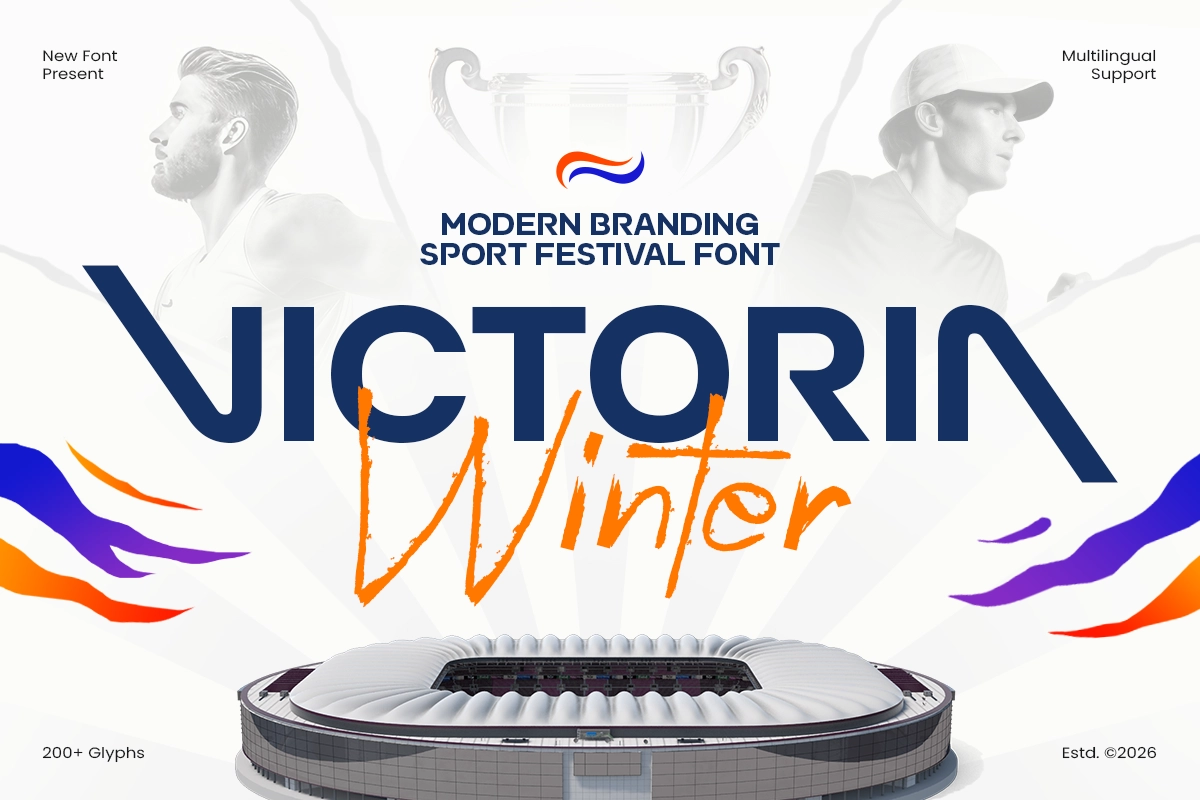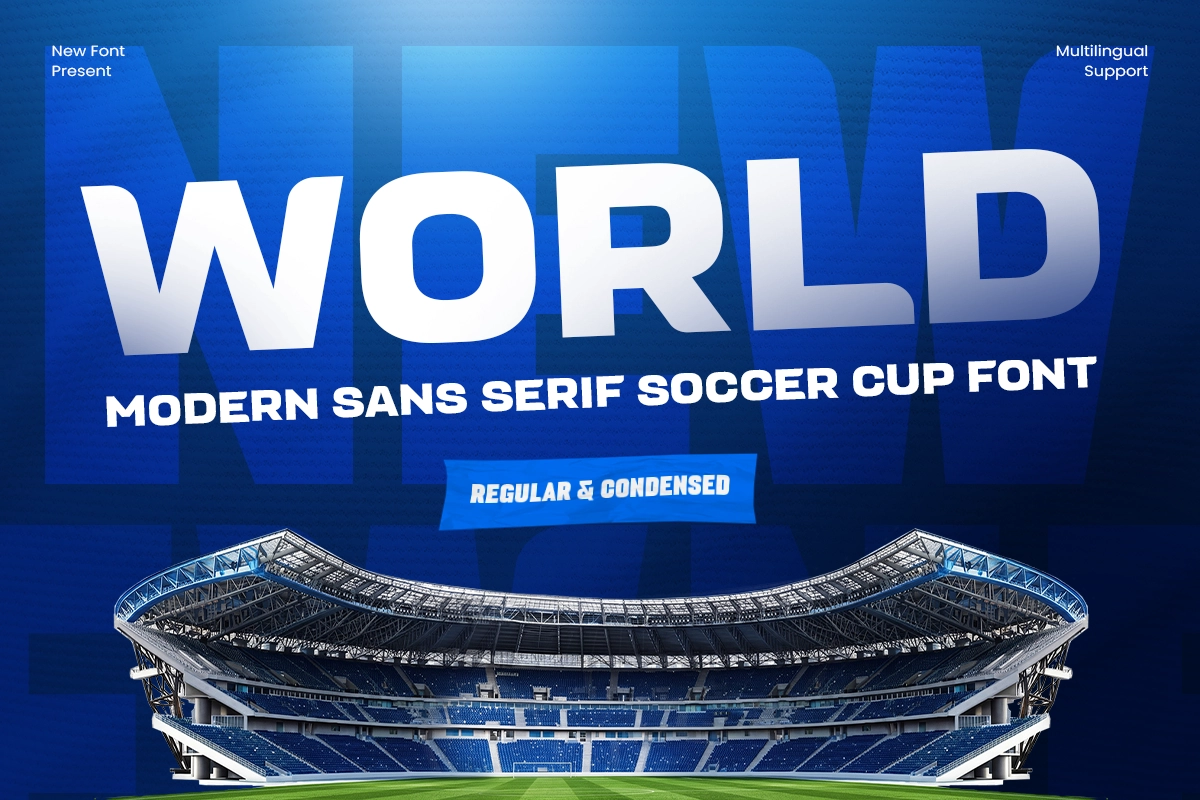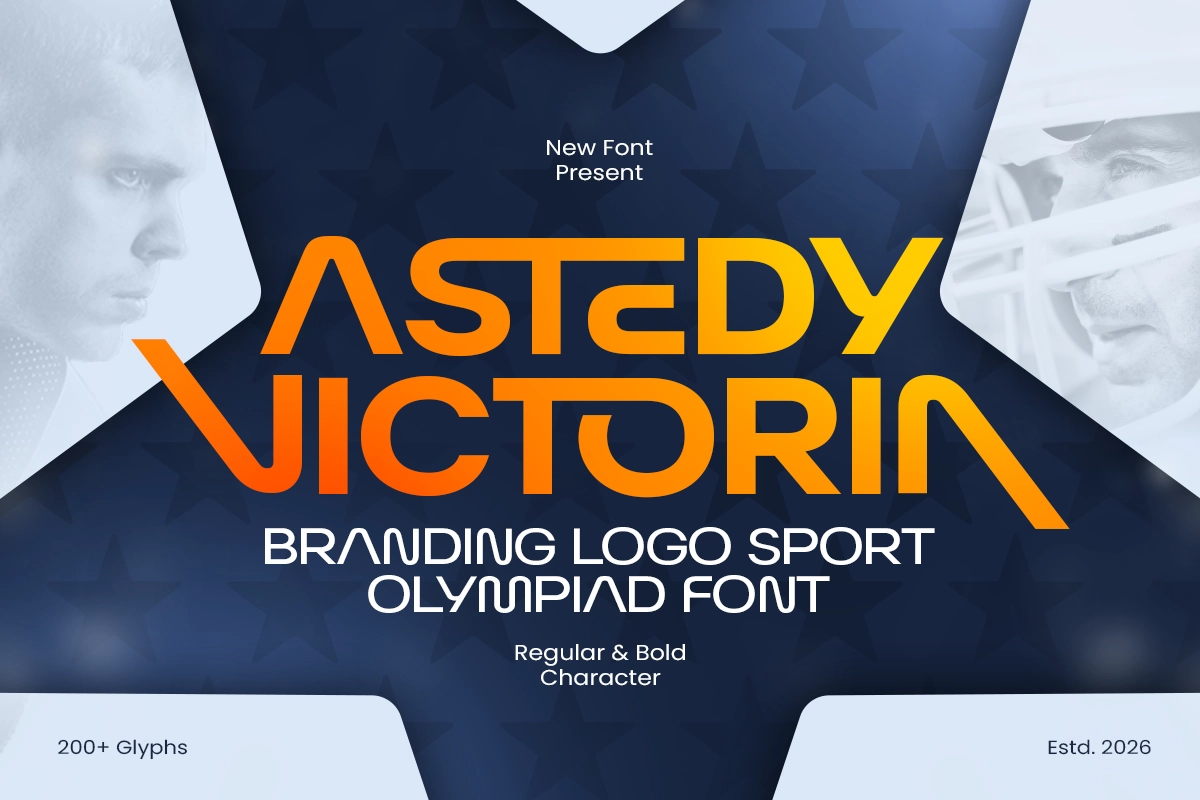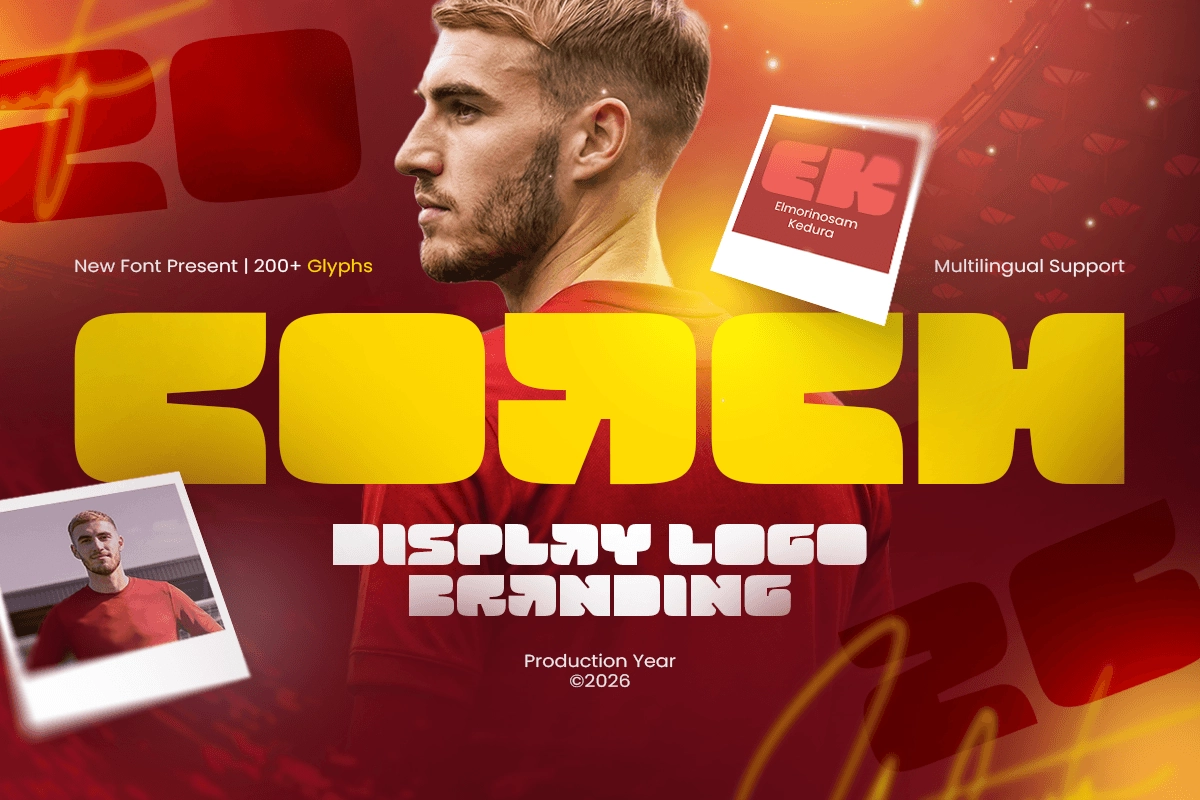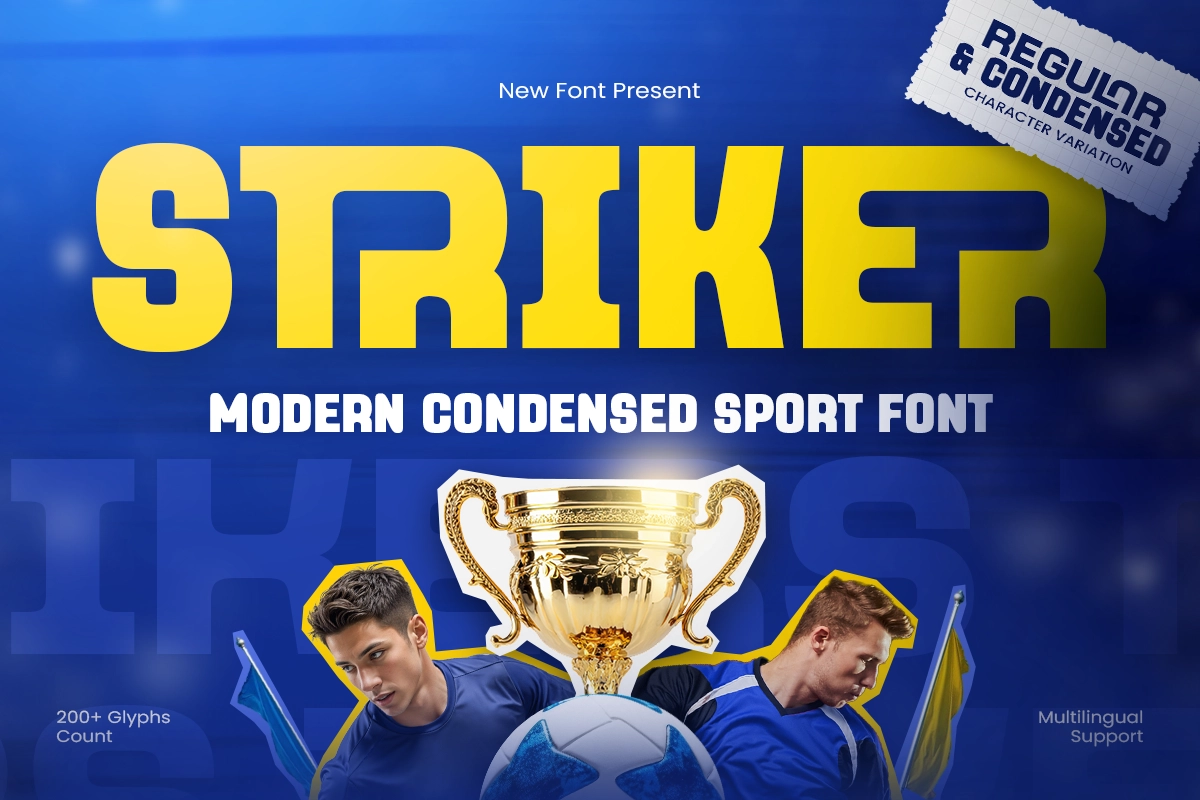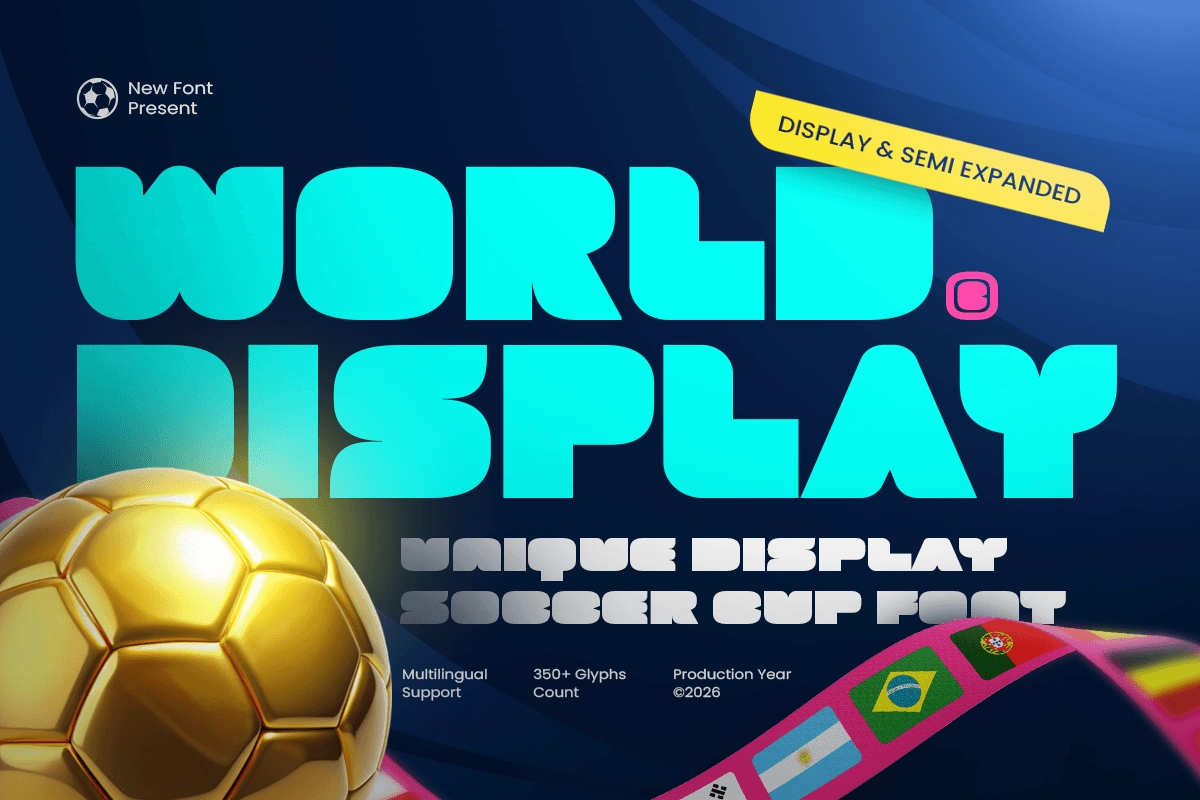
Font apa yang digunakan untuk Piala Dunia 2026?
Font Piala Dunia 2026 menggunakan typeface custom eksklusif milik FIFA yang dirancang khusus untuk identitas visual turnamen ini. Panduan ini menjelaskan mengapa desainer sebaiknya menghindari meniru font resmi tersebut, sekaligus merekomendasikan alternatif font olahraga berlisensi yang cocok untuk poster sepak bola, mockup jersey, grafis matchday, dan branding tim.
Font apa yang digunakan untuk Piala Dunia 2026?
FIFA World Cup bukan sekadar turnamen sepak bola. Setiap edisi menghadirkan sistem identitas visual yang lengkap. Mulai dari logo, warna, maskot, poster, jersey, hingga tipografi yang membentuk keseluruhan bahasa visual yang tampil di stadion, layar siaran, merchandise, dan kampanye digital.
FIFA World Cup 2026 menjadi salah satu edisi paling dinantikan karena diselenggarakan di tiga negara sekaligus: Amerika Serikat, Kanada, dan Meksiko. Dengan skala sebesar itu, identitas visual harus terasa kuat, modern, dan mudah dikenali dalam berbagai format. Tipografi menjadi elemen penting yang membawa identitas tersebut ke layar stadion, grafis siaran, merchandise, media sosial, dan materi kampanye resmi.
Bagi para desainer, font Piala Dunia 2026 menarik perhatian karena menghadirkan nuansa berani, sporty, dan berenergi tinggi yang khas dari ajang olahraga global. Namun, menggunakan typeface resmi tersebut, menjiplak bentuk hurufnya, atau meniru gayanya terlalu dekat dapat menimbulkan risiko hukum dan masalah branding. Pendekatan yang lebih aman adalah mempelajari arah visualnya, lalu memilih font olahraga berlisensi dengan energi serupa untuk poster sepak bola, mockup jersey, grafis matchday, branding tim, dan desain bertema turnamen.
Dengan turnamen yang digelar di tiga negara dengan budaya visual yang berbeda-beda, peluang kreatif terbuka sangat luas. Dari poster penggemar dan flyer nonton bareng hingga grafis profesional saluran olahraga, panduan ini menjelaskan font resmi Piala Dunia 2026 sekaligus merekomendasikan alternatif font olahraga berlisensi untuk proyek desain bertema sepak bola.
Font Apa yang Digunakan FIFA World Cup 2026?
Font resmi FIFA World Cup 2026 adalah typeface custom bernama FWC 2026, yang juga disebut FWC 26. Ini bukan font komersial biasa yang bisa diunduh dan digunakan secara bebas oleh siapa saja. Typeface ini dibuat khusus untuk turnamen dan merupakan bagian dari identitas visual resmi FIFA World Cup 26. Panduan IP (Intellectual Property) FIFA menyatakan bahwa typeface resmi tersebut dibuat untuk turnamen dan dilindungi hak cipta di mana berlaku, serta telah didaftarkan sebagai desain di berbagai yurisdiksi.
FWC 2026 mendukung identitas turnamen secara menyeluruh, mencakup grafis resmi, komunikasi kota tuan rumah, materi siaran, merchandise, dan visual kampanye publik. Karena Piala Dunia hadir di layar stadion berukuran raksasa maupun di tampilan mobile yang kecil, tipografi yang digunakan harus terasa berani, jelas, fleksibel, dan mudah dikenali secara instan.
Berbeda dari banyak font komersial, FWC 2026 tidak dirancang sebagai font publik untuk kebutuhan desain sehari-hari. Ia adalah bagian dari bahasa visual eksklusif brand FIFA World Cup 26.
Alternatif Font Piala Dunia 2026 Terbaik untuk Desainer
Bagi desainer yang ingin tampilan terinspirasi sepak bola tanpa menyalin typeface resmi FIFA World Cup 2026, Sensatype Studio menawarkan beberapa font olahraga dan display dengan struktur tebal, ritme atletis, dan energi siap turnamen. Font-font ini bukan font resmi FIFA, namun sangat cocok untuk poster sepak bola orisinal, mockup jersey, visual matchday, grafis tim, dan proyek branding olahraga.
Astedy Victoria – Branding Logo Sport Olympiad Font
Astedy Victoria - Logo Sport Festival Font
Astedy Victoria adalah font festival olahraga bold dengan nuansa seremonial yang kuat. Font ini bekerja dengan sangat baik untuk poster turnamen, grafis acara pembukaan, headline kejuaraan, dan branding olahraga yang membutuhkan suasana megah dan kompetitif.
Striker – Modern Condensed Sport Font
Striker - Modern Tall Sport Font
Striker adalah font olahraga condensed tinggi yang dirancang untuk kecepatan dan dampak vertikal. Font ini menjadi pilihan tepat untuk grafis pemain, poster matchday, tata letak terinspirasi jersey, visual susunan pemain, dan headline kampanye sepak bola yang membutuhkan tampilan cepat dan kompetitif.
World – Modern Sans Serif Soccer Cup Font
Q: Mengapa desainer mencari font Piala Dunia 2026?
A: Desainer mencari font Piala Dunia 2026 karena turnamen ini memiliki identitas visual yang berani dan mudah dikenali. Gaya tipografi sportif tersebut berguna sebagai inspirasi untuk poster sepak bola, mockup jersey, grafis matchday, dan proyek branding olahraga.